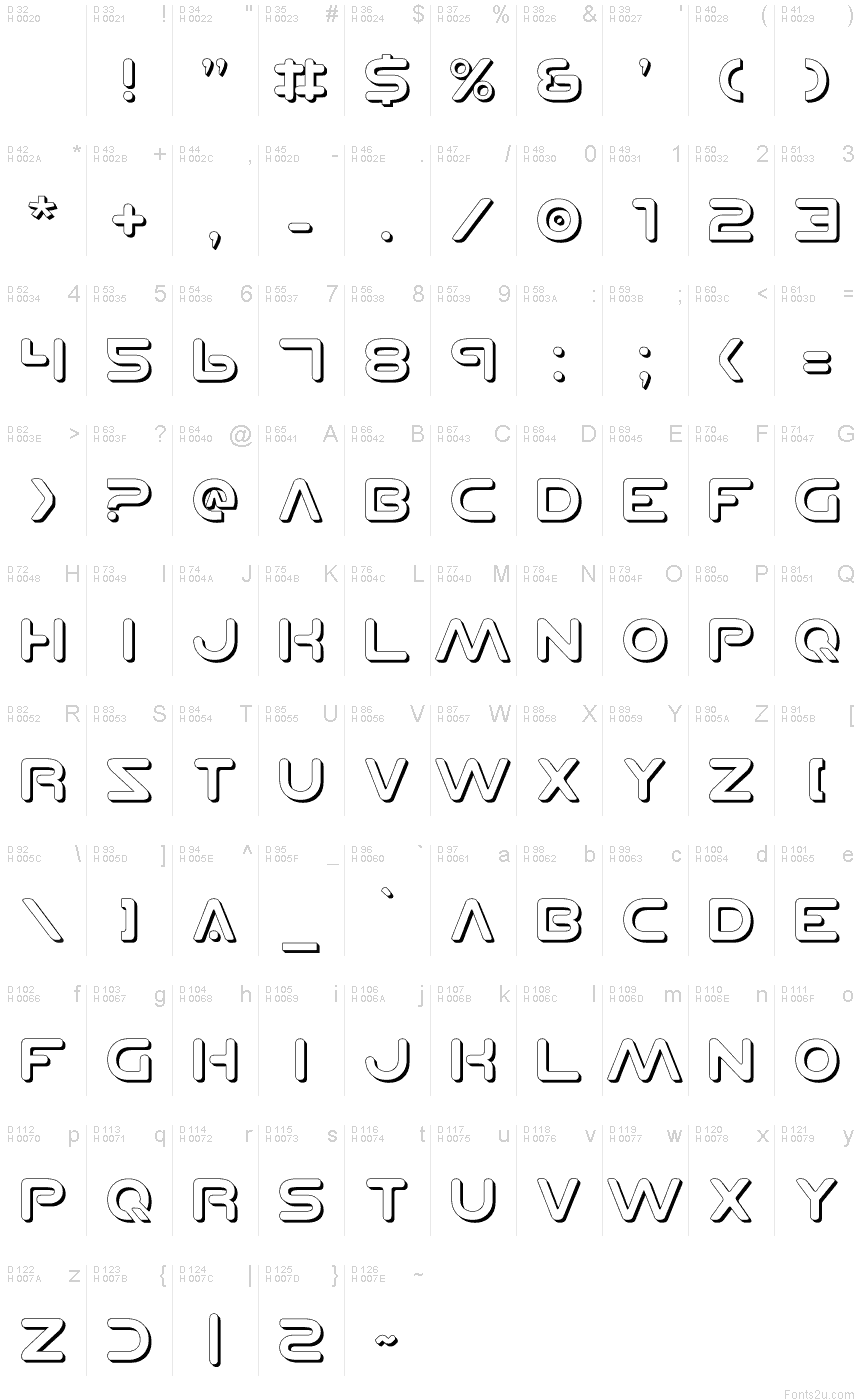
Planet N Shadow من Iconian Fonts هو خط عرض (display font) مجاني، مستقبلي، يعتمد الحروف الكبيرة (Caps) ويتمتع بطابع فضاء كلاسيكي أنيق. تتكون الحروف من ضربات دائرية أنبوبية مقترنة بظل جانبي حاد، مما يمنح الأبجدية مظهر لافتة النيون المعلقة: مظهر نظيف، مرح، ويحاكي أجواء ألعاب الأركيد.
يتناسب هذا الخط بشكل طبيعي مع ملصقات الخيال العلمي، وشعارات الألعاب، ومنشورات النوادي، وبطاقات العناوين، والنصوص التقنية حيث تحتاج العبارات القصيرة إلى تلك اللمسة المضيئة ذات الأبعاد. وبكونه خطاً مجانياً، فهو يعمل بشكل ممتاز أيضاً للمونوغرامات والحروف الاستهلالية، لأن معالجة الظل تمنح حتى بضعة أحرف حضوراً قوياً دون الحاجة إلى مؤثرات إضافية.